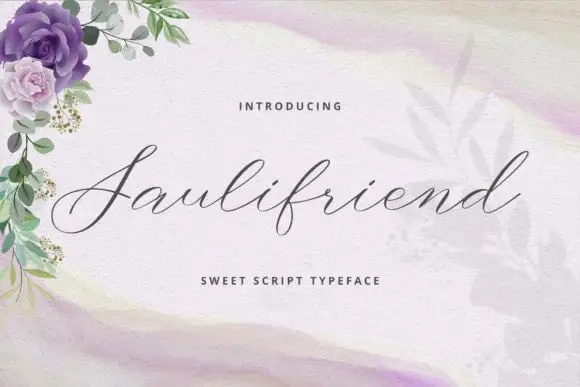
Saulifriend Calligraphy Font – Download Grátis
A Saulifriend Calligraphy Font é uma escolha excepcional para designers buscando elegância e estilo em seus projetos gráficos. Nesse script-font, você encontra linhas suaves e uma variedade de linhas do ponto baselines, criando um visual que se destaca não apenas nas cartas de agradecimento ou convites de casamento, mas também nos logotipos, identidades corporativas, mensagens e qualquer outro projeto gráfico que precise de uma pitada autêntica de letra à mão. Desenvolvida pelo sartstudio na 99designs, essa font oferece uma paleta rica de glyphs agradáveis aos olhos, junto com alternativas excepcionais para garantir um resultado final ainda mais profissional e único. Seja você um designer de cartões de aniversário ou um estilista de moda, esta font é perfeita para incorporar um toque autêntico em seu trabalho, transformando cada design num ato de criatividade com profundidade.